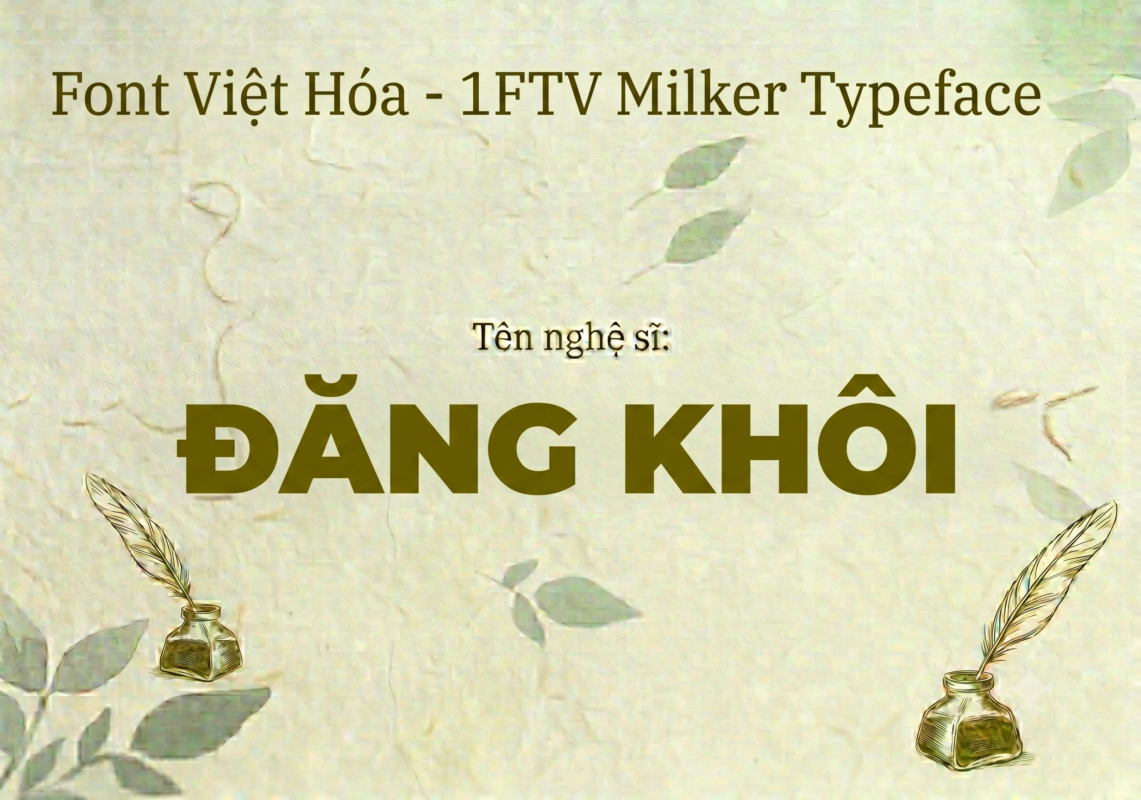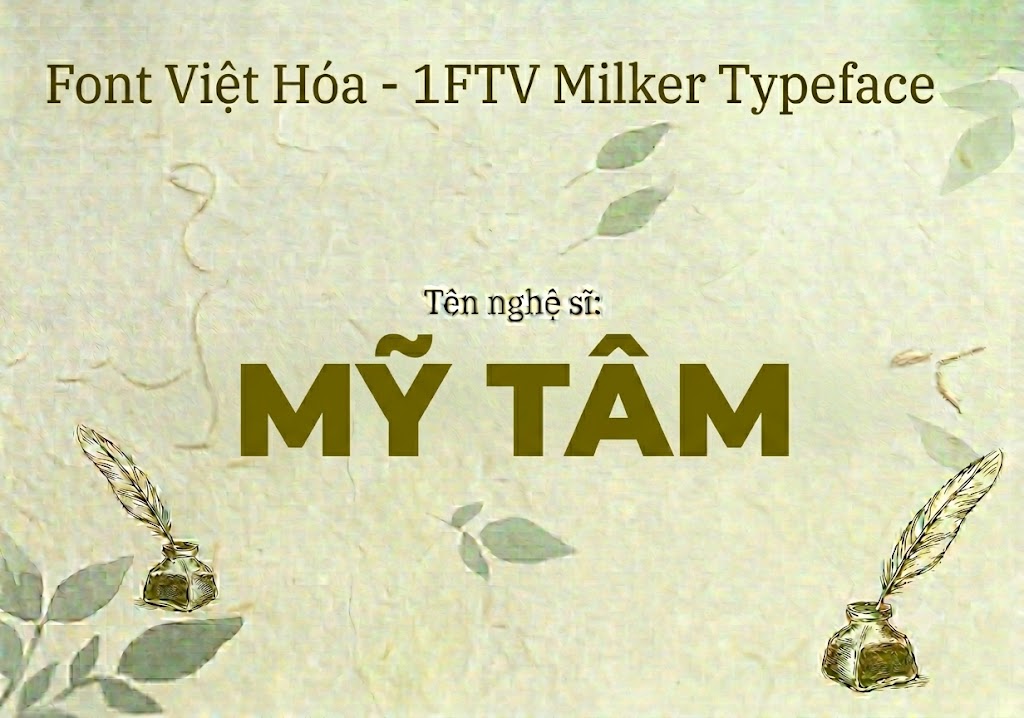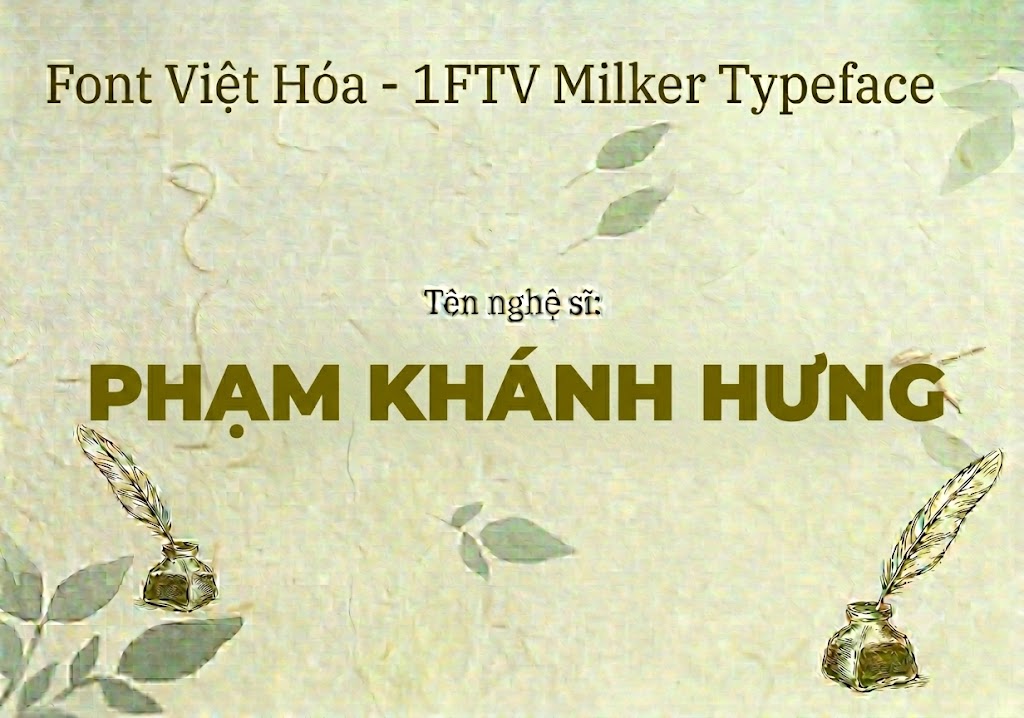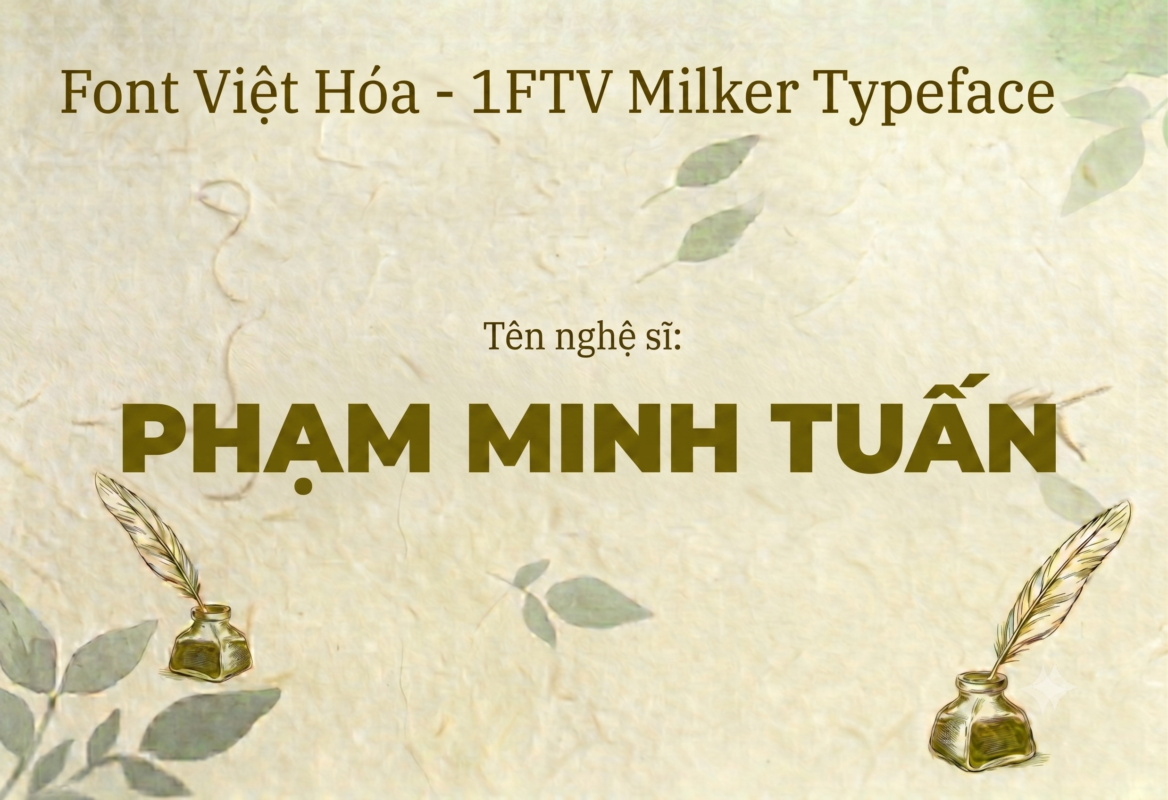
1FTV Milka
Trong bối cảnh sáng tạo nội dung số ngày càng cạnh tranh, việc lựa chọn một phông chữ làm tiêu đề vừa dày dặn, dễ đọc lại vừa có sức nặng thị giác lớn là yếu tố quyết định để giữ chân người xem. Hôm nay, chúng tôi xin giới thiệu đến bạn một bộ chữ display không thể bỏ qua trong bộ sưu tập của mình, đó chính là font 1FTV Milker.
Đây là một giải pháp hoàn hảo để tạo nên các dòng tiêu đề giật tít, các mẫu ảnh thu nhỏ (thumbnail) có tỷ lệ nhấp chuột cao hoặc các sản phẩm bao bì quảng cáo mang phong cách trẻ trung, năng động. Với cấu trúc các nét chữ siêu dày (ultra-bold) nhưng vẫn giữ được sự mềm mại mượt mà, font 1FTV Milker chắc chắn sẽ là trợ thủ đắc lực giúp nâng tầm các dự án thiết kế của bạn.
Giới thiệu về font 1FTV Milker
Font 1FTV Milker là một phông chữ thuộc thể loại display (hiển thị) không chân, nổi bật với phom chữ đầy đặn, vững chãi và mang lại cảm giác vô cùng thân thiện, hiện đại. Bộ font này được hoàn thiện kỹ lưỡng ở phiên bản 1.001 thông qua công cụ tạo font chuyên nghiệp Fontself Maker 3.5.8.
Sản phẩm được định dạng theo chuẩn opentype layout tiên tiến, tích hợp sẵn chứng thực kỹ thuật số (digitally signed) và sở hữu các đường nét vector chuẩn postscript outlines. Nhờ vậy, phông chữ luôn đảm bảo độ sắc nét tuyệt đối, không bị nhòe hay mờ cạnh ngay cả khi bạn hiển thị trên màn hình độ phân giải cao hoặc mang đi in ấn khổ lớn. Bản font này được chia sẻ rộng rãi bởi đội ngũ 1FTV để phục vụ cho cộng đồng designer tại Việt Nam.
Đặc điểm nổi bật của phong cách thiết kế Milker
Sức hút đặc biệt của font 1FTV Milker đến từ độ dày nét chữ tối đa nhưng cấu trúc tổng thể lại vô cùng gọn gàng, hài hòa. Không quá cứng nhắc như các dòng font hình khối khác, các góc của chữ Milker được bo nhẹ tinh tế, tạo nên cảm giác căng mọng, đầy đặn và tràn đầy năng lượng đúng như tên gọi của nó.
Phông chữ được thiết kế theo cấu trúc all-caps (viết hoa toàn bộ các chữ cái), giúp các nhà thiết kế dễ dàng sắp xếp bố cục tiêu đề mà không sợ bị lệch cao độ hay mất cân đối giữa các dòng chữ. Khoảng hở bên trong (counter) của các ký tự như O, D, B, A được tính toán tỷ lệ rất chuẩn, giúp chữ không bị dính nét hay bị đặc khối khi nhìn từ khoảng cách xa.
Để phông chữ hoạt động mượt mà trên mọi hệ thống máy tính và các phần mềm đồ họa, phiên bản font 1FTV Milker đã trải qua quá trình căn chỉnh thông số kỹ thuật tối ưu.
Đội ngũ kỹ thuật đã xử lý chính xác khoảng cách giữa từng con chữ (kerning) và độ giãn dòng (tracking), đảm bảo văn bản hiển thị liền mạch và đẹp mắt. Bên cạnh hệ thống chữ cái viết hoa đồng đều, bộ font còn tích hợp trọn vẹn dãy số từ 0-9 cùng các ký tự đặc biệt, dấu câu thông dụng (.,;: ' " (!?) +-*/=), giúp bạn thoải mái sáng tạo nội dung đa dạng mà không lo bị lỗi định dạng hay thiếu ký tự khi gõ.
Hình ảnh demo thực tế của font 1FTV Milker
Để giúp bạn có cái nhìn trực quan nhất về khả năng co giãn và hiển thị của phông chữ này trên các kích thước khác nhau, hãy cùng xem qua bảng mô phỏng thực tế:
Kích thước nhỏ (12pt – 24pt):
Các đường nét siêu đậm vẫn giữ được sự rõ ràng, phom chữ ngay ngắn và cực kỳ dễ đọc trên màn hình điện thoại.
Kích thước lớn (36pt – 72pt): Đây là không gian lý tưởng
để font chữ phô diễn toàn bộ sự mạnh mẽ của mình, tạo hiệu ứng thị giác đè nặng và thu hút sự chú ý ngay lập tức.
Ứng dụng của font Milker trong thiết kế đồ họa và làm video
Với phong cách thiết kế siêu đậm đầy ấn tượng, font 1FTV Milker mở ra không gian ứng dụng vô cùng linh hoạt cho các dự án truyền thông và marketing:
Thiết kế thumbnail và
ảnh thu nhỏ: Đây chính là vũ khí hạng nặng để làm nổi bật tiêu đề trên thumbnail Youtube, Tiktok hay Facebook. Chữ sẽ cực kỳ nổi bật khi bạn đổ thêm màu tương phản cao (vàng, trắng, xanh neon) trên các phần nền tối.
Làm tiêu đề cho video ngắn (Shorts, Reels, Tiktok): Font chữ này cực kỳ thích hợp để làm các cụm
từ key-word chính hoặc phụ đề chạy chữ sinh động, giúp người xem lướt qua là có thể nắm bắt được thông điệp ngay.
Thiết kế bao bì và bộ nhận diện thương hiệu: Rất phù hợp cho các ngành hàng thực phẩm, đồ uống (
đặc biệt là sữa, bánh ngọt, trà sữa), đồ chơi trẻ em hoặc các sản phẩm sáng tạo cần sự vui nhộn, béo tròn mộc mạc.
Banner và poster quảng cáo: Thích hợp cho các
poster chương trình khuyến mãi, banner sự kiện giải trí cần truyền tải thông điệp ngắn gọn, trực diện và mạnh mẽ.